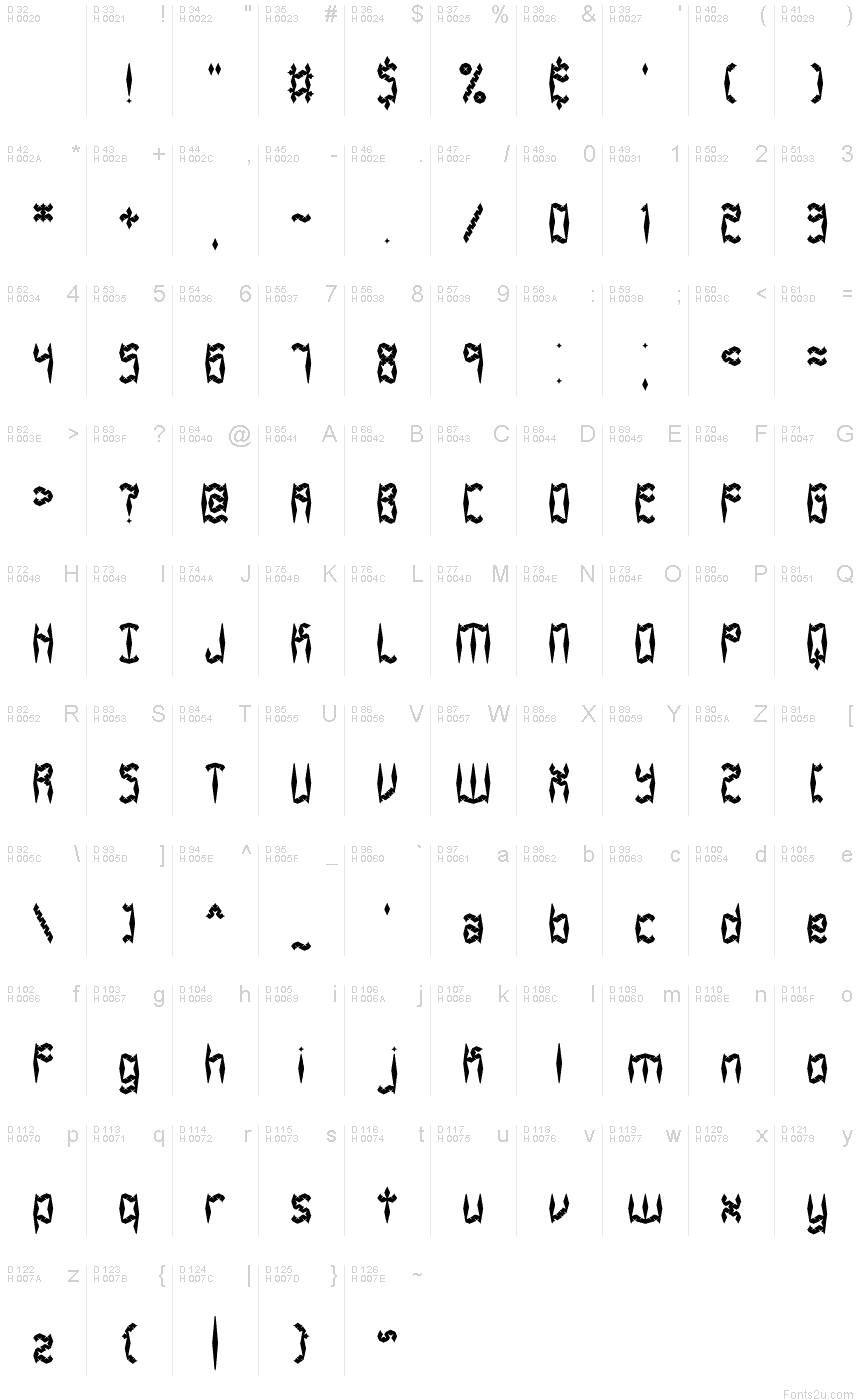
خط Zirconia من AEnigma Fonts هو خط عرض مجاني يتميز بأسلوب البلورات المقطوعة وإيقاع حاد ومتعدد الأوجه. تبدو الحروف وكأنها منحوتة من الحجر أو مطوية من شظايا حادة، مع وصلات مدببة وشقوق زاوية تتكرر في جميع أنحاء المجموعة، مما يمنح الكلمات طابعاً هشاً وحاداً ومتمرداً بعض الشيء.
يناسب الخط منشورات الحفلات الموسيقية، وأغلفة كتب الفانتازيا، وعناوين الألعاب، وعناوين الملصقات، وتجارب الشعارات حيث يساعد المظهر المعدني الخشن في تحديد الحالة المزاجية بسرعة. وباعتباره خطاً مجانياً، فهو يعمل بشكل أفضل في العناوين القصيرة والشعارات المختصرة والكلمات البارزة، لأن هذه الصور الظلية المتكسرة تنقل شخصية الخط بشكل أكثر إقناعاً مما تفعله في فقرات النصوص الطويلة.